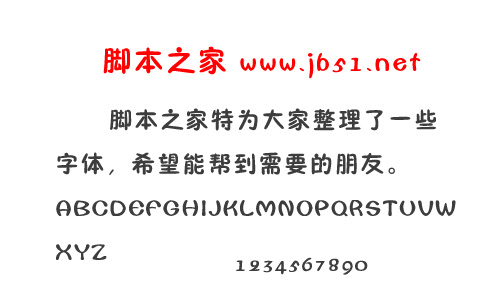
方正少兒簡體字體是方正字體庫中的一種字體,方正少兒的設(shè)計意在模仿少兒寫字的特點(diǎn)。這款字體的筆畫圓潤稚拙,字形輪廓整體統(tǒng)一,具有一定的易讀性。方正少兒的個性純真稚氣,適用于少兒類的書刊、品牌廣告和產(chǎn)品包裝設(shè)計,以及社交網(wǎng)絡(luò)的個性化用字,還可勝任簡短的正文排版。喜歡的朋友們可以前來下載使用。